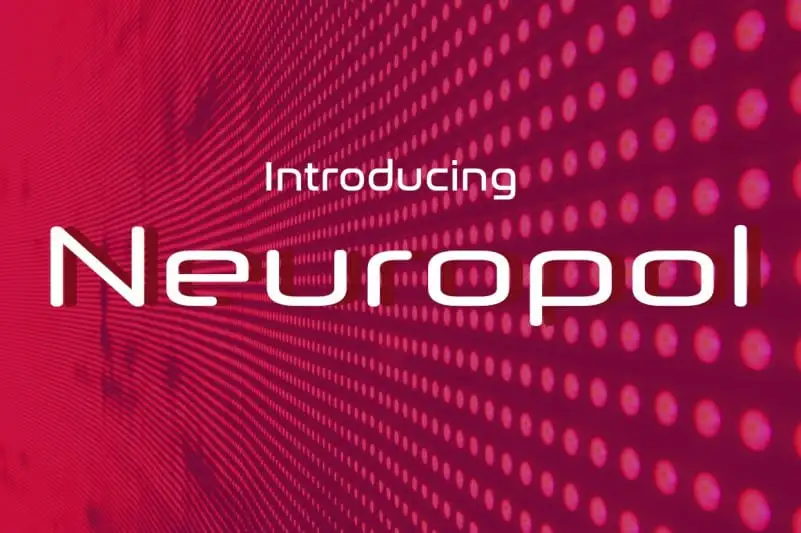
A Neuropol Typeface é uma fonte futurista e vibrante que surgiu no início dos anos 90. Criada em 1996 pelo designer Hamilton, essa tipografia se destaca por seus quadrados redondos inspirados nos fonts techno da década de 80, como Microgramma, Digital e Chimes. Suas bordas curvadas proporcionam um aspecto harmônico ao texto, enquanto os traços truncados sugerem lasers ou marcas vectuais. Desde sua criação em 1996, a Neuropol teve várias releituras, sendo expandida para a Neuropol X no ano de 2004. Em 2015, o original da década foi restaurado e re-lançado com várias melhorias, incluindo novos sinais monetários e um @ mais acentuado. Esta fonte é perfeita para aplicativos que suportam alternativas estilizadas em OpenType, oferecendo um Z completo semelhante ao encontrado na Neuropol X. A Neuropol Typeface encanta por sua simplicidade moderna e elegância futurista, tornando-a uma opção inovadora para projetos digitais contemporâneos.